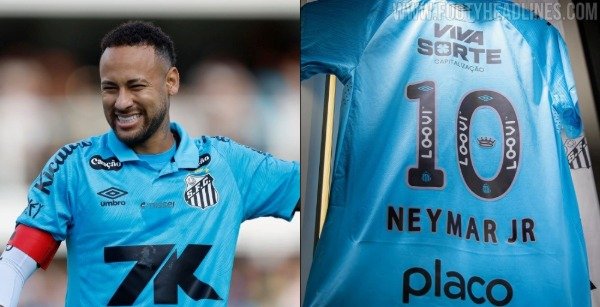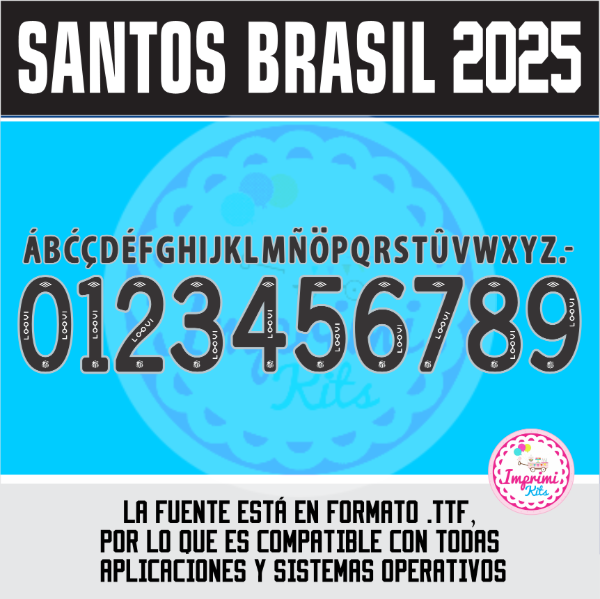
Tipografía Números Fuente Camisetas SANTOS DE BRASIL 2025
Tipografía Números Fuente
Los vectores de numeros dorsales incluyen detalles y el logo oficial en el numero